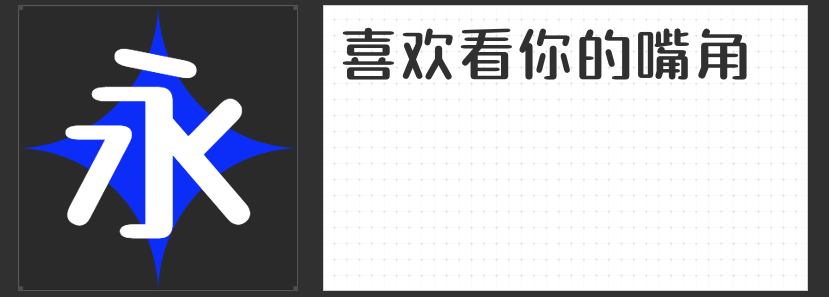
四款高辨识度创意字体推荐:为电商设计注入童趣与个性
在电商视觉竞争白热化的今天,独特的字体设计能瞬间抓住消费者眼球,传递品牌温度。以下四款商用字体虽需授权,却以鲜明的风格与高适配性,成为儿童用品、潮流品牌、文创周边等品类的设计利器。
一、励字笑语声声简
这款字体以孩童稚拙笔触为灵感,笔画圆润无尖角,布白均匀中透着天然萌感。弧形转角与适度留白营造出“手作温度”,既能驾驭母婴产品页面的温馨氛围,也能为零食包装增添趣味标签。其高辨识度在缩略图展示时优势显著,是打破同质化设计的利器。
二、励字圆梦简 中黑
作为三字重家族字体,中黑版本以直线架构融合圆弧收笔,形成“外圆内方”的独特气质。松散的中宫设计让长段落阅读更舒适,而简洁的竖折笔画又保留了黑体的现代感。无论是电子设备详情页的技术参数排版,还是家居品牌的生活场景海报,都能通过字重调节实现标题与正文的视觉连贯。
三、字恋狂嗨玩简
粗壮笔画与方块字形赋予字体强烈的玩具质感,重心下沉设计更显稳重憨厚。这种“笨拙可爱”的气质与潮玩、电竞外设等品类高度契合,尤其适合作为促销弹窗的标题字体。其积木般的视觉语言还能延伸出动态排版效果,为直播封面或社交媒体素材增添互动感。
四、字恋狂灵怪简
将几何图形解构重组的折笔处理,搭配流畅的连笔设计,让这款字体充满天马行空的想象力。古灵精怪的笔触走向既能表现文创品牌的艺术调性,也能为宠物用品页面注入活泼气息。在需要突出产品差异化的场景中,其独特的视觉符号能快速建立品牌记忆点。
这四款字体通过差异化的设计语言,为电商设计提供了丰富的表达维度。从童趣手写到几何解构,从温馨叙事到潮流态度,设计师可根据品牌调性灵活选择,让字体成为传递价值的第一视觉触点。